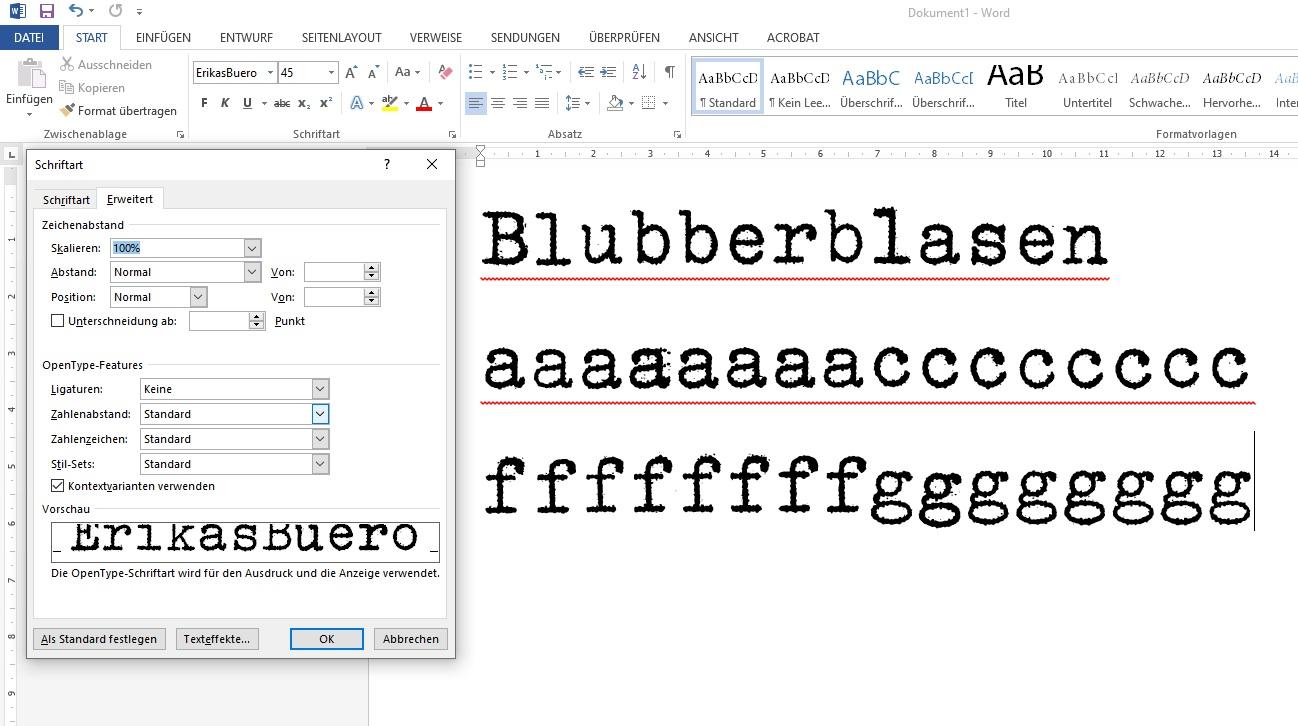
Humanizer für Schriften
Erikas Büro läuft bei mir (W10, Word 2013) ziemlich gut, wenn man die „Kontextvarianten“ aktiviert.
Kannst Du Deinen Testtext hier einmal zum Runterladen einstellen? Das würde ich sehr gerne mal nachvollziehen, ob es bei mir dann doch funktioniert oder nicht.
Reicht das so?
Lieben Dank. Ich hatte es ursprünglich mit Erikas Farbband probiert - damit geht es nicht. Mit Erikas Büro klappt es. In der Beschreibung beider Schriften wird dieser Effekt aber gleich beschrieben. @catfonts Wo ist der Unterschied? Ich will das nur verstehen, damit ich weiß, worauf ich beim Kauf von Schriften achten muss.